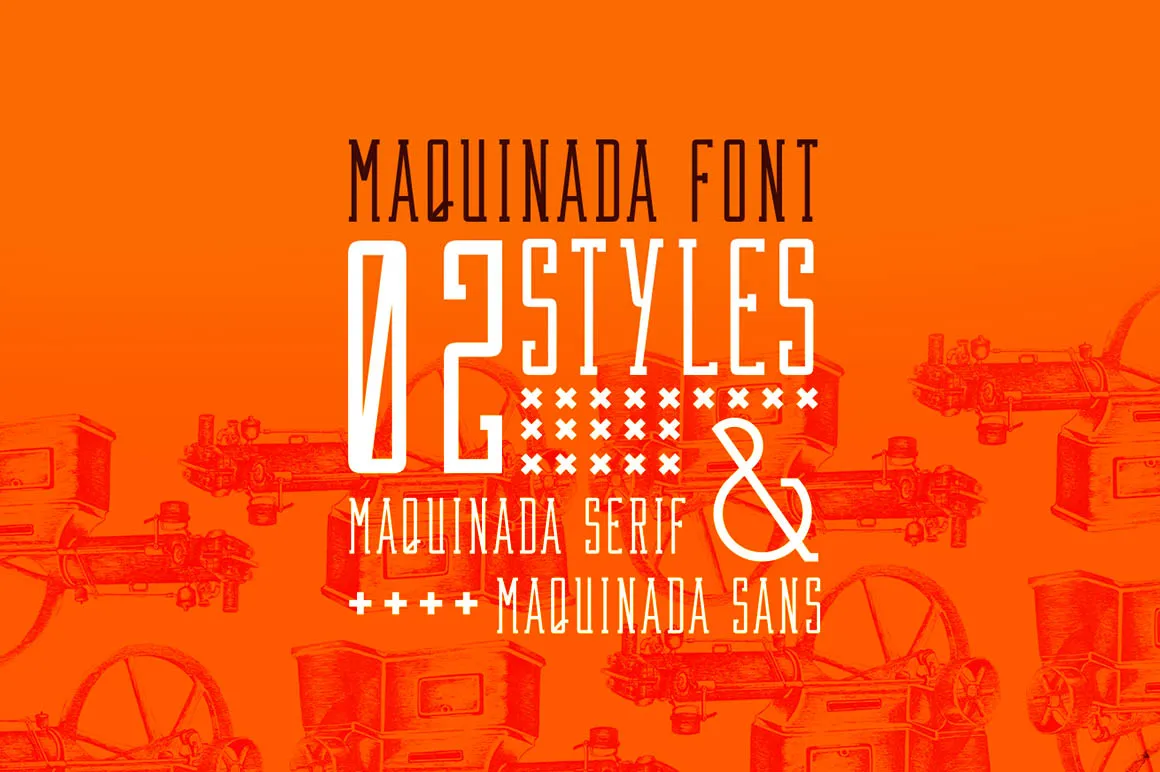
A Maquinada Font é uma elegante fonte serif que surgiu para os alunos do segundo ano de Design Gráfico na Universidade Estadual de Londrina, no Brasil. Inspirada na disciplina de tipografia, essa fonte foi projetada pensando em quem a usará – estudantes e profissionais buscando um estilo formal e sofisticado. Com linhas suaves e detalhes cuidadosamente planejados, ela é perfeita para trabalhos acadêmicos, manuais e qualquer aplicação que valorize um tom mais elegante e formal. Ideal para quem busca uma fonte com forte identidade visual que seja tanto profissional quanto bonita. Acredite em sua capacidade de criar layouts ricos, seletivos e acima de tudo, legíveis sob qualquer tipo de condição de leitura. Essa é uma opção perfeita para aqueles que buscam uma fonte serif com um charme sofisticado, ideal para quem deseja dar um toque final aos projetos gráficos mais formais.